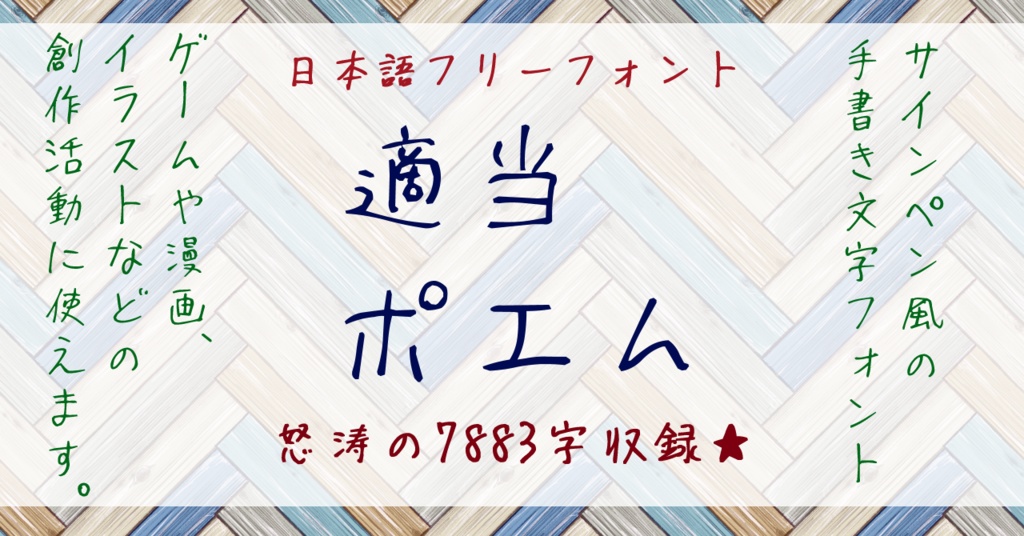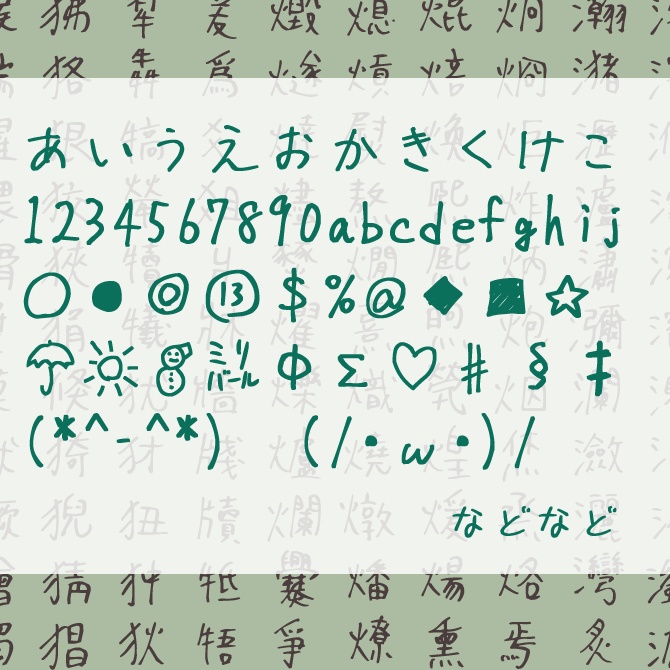
一款合适的日语手写字体。它收录了包括英文字母和数字、平假名、片假名、JIS第1至4级汉字以及其他汉字和符号等约16000个字符。这款字体适用于游戏、插图、动画、印刷品等多种用途。每个字符的大小和精细度都有所不同,呈现出独特的手写风格。
“適当ポエム1.043”是一款书写很新颖的字体,字体大方,适合各种设计作品使用!欢迎下载!